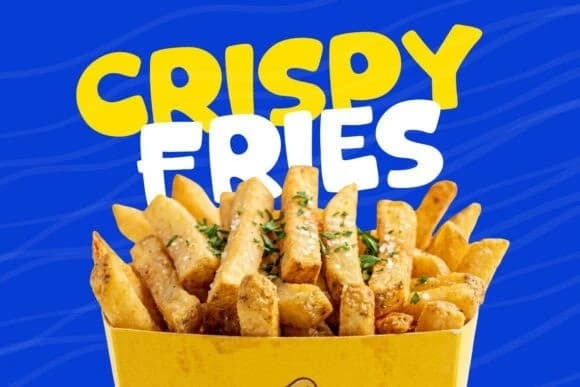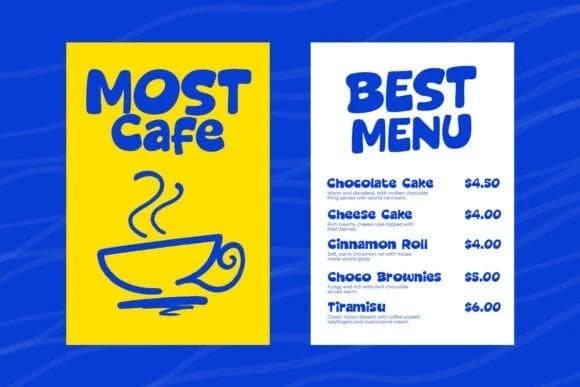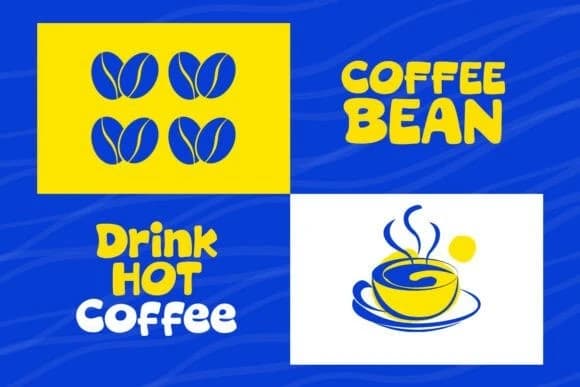
Trend Bold Font
Trend Bold Font, posterler, logolar, dergiler, kapaklar, afişler ve daha fazlası için mükemmel olan modern ve sevimli bir gösterim yazı tipidir! Bu muhteşem fontu edinin ve güzel tasarımlar yaratmak için kullanın. Projelerin inanılmaz geniş bir yelpazesine kolayca uyum sağlar.
Trend Bold Font, posterler, logolar, dergiler, kitap kapakları, afişler ve daha pek çok şey için mükemmel olan modern ve sevimli bir gösterim yazı tipi! Bu harika fontu edinin ve güzel tasarımlar oluşturmada kullanın. İnanılmaz derecede geniş bir proje yelpazesine kolayca uyum sağlar.